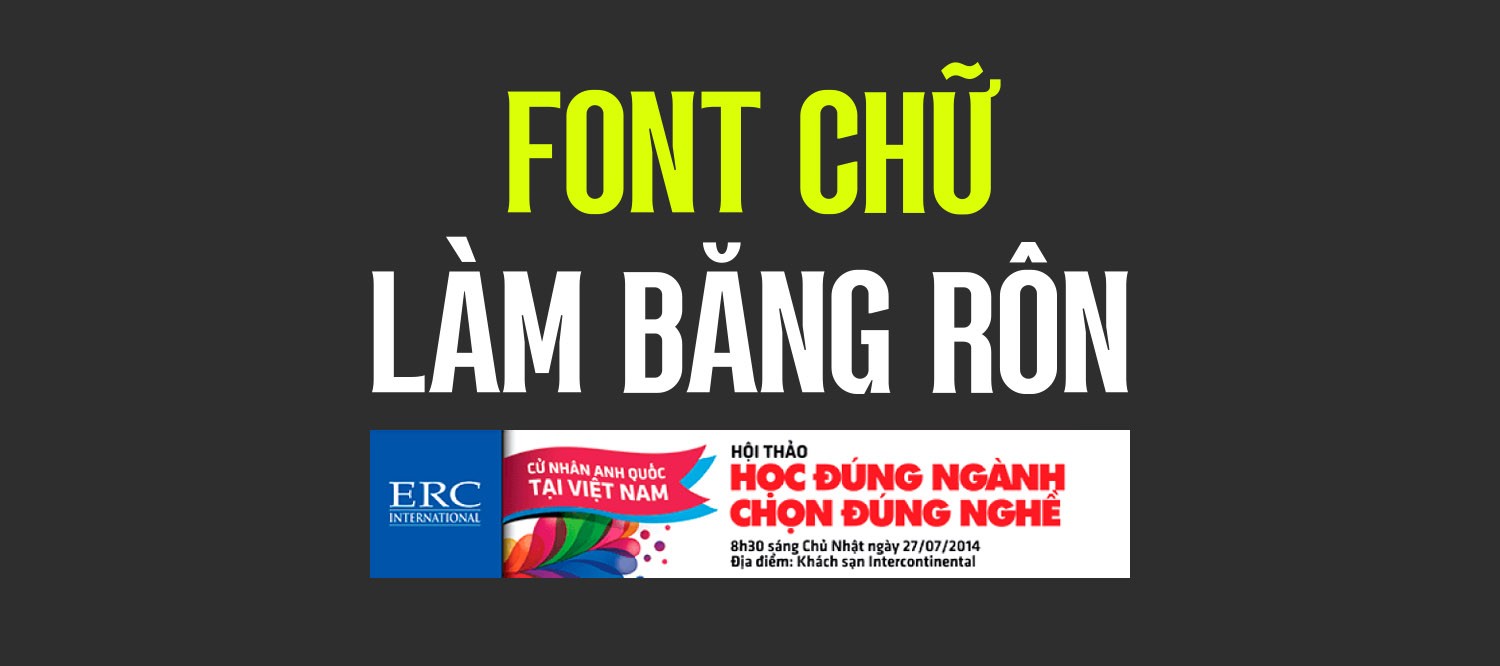
[Tải xuống] Tổng hợp 10+ font chữ cho thiết kế băng rôn, background đẹp nhất 2025
Trong thế giới thiết kế đồ họa, lựa chọn font chữ đóng một vai trò cực kỳ quan trọng trong việc tạo dựng ấn tượng đầu tiên. Đặc biệt, với những dự án thiết kế liên quan đến banner, băng rôn hay các quảng cáo ngoài trời, font chữ trở thành một yếu tố không thể thiếu để truyền tải thông điệp một cách rõ ràng và thu hút. Trong bài viết này, chúng tôi sẽ cập nhật bộ font chữ băng rôn đẹp nhất, giúp bạn dễ dàng chọn lựa và tải về để phục vụ cho các dự án thiết kế của mình.
Font chữ quân đội cứng cáp TH Westorn
Font chữ quân đội TH-Westorn mang đến cảm giác mạnh mẽ và cứng cáp, rất phù hợp cho các thiết kế băng rôn có chủ đề quân sự, sự kiện thể thao hoặc quảng cáo mạnh mẽ. Font chữ này có nét chữ sắc bén, dễ đọc và tạo cảm giác mạnh mẽ ngay từ cái nhìn đầu tiên. Sử dụng font chữ này, bạn có thể dễ dàng tạo ra các băng rôn nổi bật và thu hút sự chú ý của người xem.
Font chữ hiện đại cứng cáp TH Futurama
Nếu bạn đang tìm kiếm một font chữ băng rôn hiện đại, trẻ trung và phù hợp với các sự kiện thể thao, font chữ TH Futurama sẽ là một lựa chọn tuyệt vời. Được thiết kế với các đường nét góc cạnh, font chữ này tạo cảm giác năng động, mạnh mẽ, rất thích hợp cho các thiết kế băng rôn quảng bá sự kiện thể thao, các trận đấu hoặc các chiến dịch quảng cáo về thể thao.
Font chữ chủ đề lịch sử TH Lichsu 3
Font chữ này là sự lựa chọn lý tưởng cho các thiết kế băng rôn có yếu tố lịch sử, văn hóa hoặc những dự án nghiên cứu, giáo dục. Với kiểu chữ cổ điển, font chữ này mang lại cảm giác trang nghiêm và tôn kính. Nó sẽ là một lựa chọn tuyệt vời cho những băng rôn giới thiệu sự kiện lịch sử, bảo tàng, triển lãm hoặc các chương trình giáo dục.
Font chữ cứng hiện đại TH Cungcap 2
Một lựa chọn tuyệt vời cho các dự án thiết kế băng rôn có tính chất mạnh mẽ, quyết liệt. Font chữ TH Cungcap 2 được thiết kế với các nét đậm, rõ ràng và dễ đọc từ xa. Đây là sự lựa chọn lý tưởng cho những thiết kế băng rôn quảng cáo sản phẩm, sự kiện nổi bật hay các chiến dịch truyền thông mạnh mẽ.
Font chữ thời trang sang trọng hiện đại TH Glowen
Font chữ này mang phong cách thời trang sang trọng và hiện đại, rất phù hợp cho các thiết kế băng rôn liên quan đến thời trang, các sự kiện cao cấp hoặc các chiến dịch quảng cáo cho các sản phẩm xa xỉ. Với những đường nét thanh mảnh và tinh tế, font chữ Glowen chắc chắn sẽ giúp các băng rôn của bạn nổi bật và thu hút sự chú ý từ xa.
Font chữ Slab Serif cứng cáp TH Blayzer
Nếu bạn đang tìm kiếm một font chữ băng rôn mạnh mẽ với kiểu dáng slab serif, thì font chữ Blayzer sẽ là sự lựa chọn lý tưởng. Font chữ này mang đến cảm giác chắc chắn, mạnh mẽ và có thể sử dụng cho các băng rôn quảng cáo sản phẩm hoặc sự kiện lớn. Kiểu chữ này dễ đọc và tạo sự ấn tượng mạnh mẽ đối với người xem.
Font chữ cứng cáp mạnh mẽ TH Bladus Slant
Font chữ Bladus Slant là một lựa chọn tuyệt vời cho các thiết kế băng rôn có chủ đề thể thao, tốc độ hoặc các sự kiện quảng bá sản phẩm công nghệ, xe cộ. Với các đường nét nghiêng, font chữ này tạo cảm giác chuyển động mạnh mẽ và tốc độ, rất thích hợp để thu hút sự chú ý của người xem.
Font chữ hiện đại không chân TH Qaz
Font chữ Qaz mang đến một phong cách hiện đại, gọn gàng và dễ đọc, không có chân, rất phù hợp cho các thiết kế băng rôn quảng cáo cho các sản phẩm công nghệ, sự kiện giới trẻ hoặc các chiến dịch Marketing sáng tạo. Font chữ này dễ dàng tạo ra những băng rôn đơn giản nhưng vẫn nổi bật.
Font chữ thanh lịch, hiện đại, sang trọng Neue Einstellung
Font chữ Neue Einstellung mang lại một phong cách thanh lịch, hiện đại và sáng tạo  lấy cảm hứng từ hiệu ứng Einstellung. Bao gồm 9 kiểu từ Thin đến Black và hỗ trợ Tiếng Việt, font này phù hợp cho các thiết kế băng rôn cao cấp, đặc biệt là trong ngành thời trang, tiệc cưới và các sự kiện sang trọng. Font chữ này giúp tạo ra một ấn tượng mạnh mẽ và quý phái cho các băng rôn của bạn.
Font chữ hiện đại Sans Serif Tonos Mono
Font chữ Tonos Mono là một kiểu font chữ hiện đại thuộc dòng Sans Serif, nhưng đặc biệt ở điểm nó có dạng mono (monospace), tức là mỗi ký tự có độ rộng bằng nhau. Đây là một đặc điểm quan trọng, làm cho Tonos Mono rất lý tưởng cho các băng rôn mang tính chất chuyên nghiệp, công nghệ hoặc các sự kiện có tính chất trang trọng như hội thảo, hội nghị, hoặc các sự kiện giới thiệu sản phẩm kỹ thuật. Với đặc điểm monospace, Tonos Mono giúp các thiết kế trở nên gọn gàng và dễ đọc ngay cả khi thông điệp dài hoặc có nhiều chữ số.
Bên cạnh đó, nếu bạn cần một font chữ background để làm nền cho các thiết kế của mình, đừng quên tham khảo thêm các font chữ phù hợp với phong cách của từng dự án. Với những font chữ này, bạn chắc chắn sẽ tạo ra những sản phẩm thiết kế tuyệt vời, giúp truyền tải thông điệp một cách rõ ràng và ấn tượng.